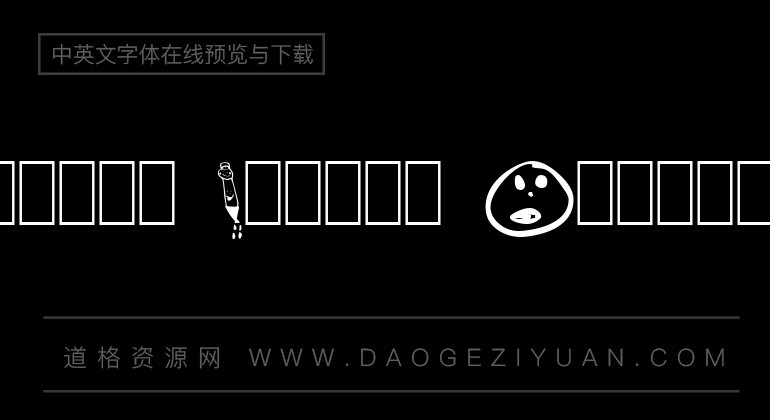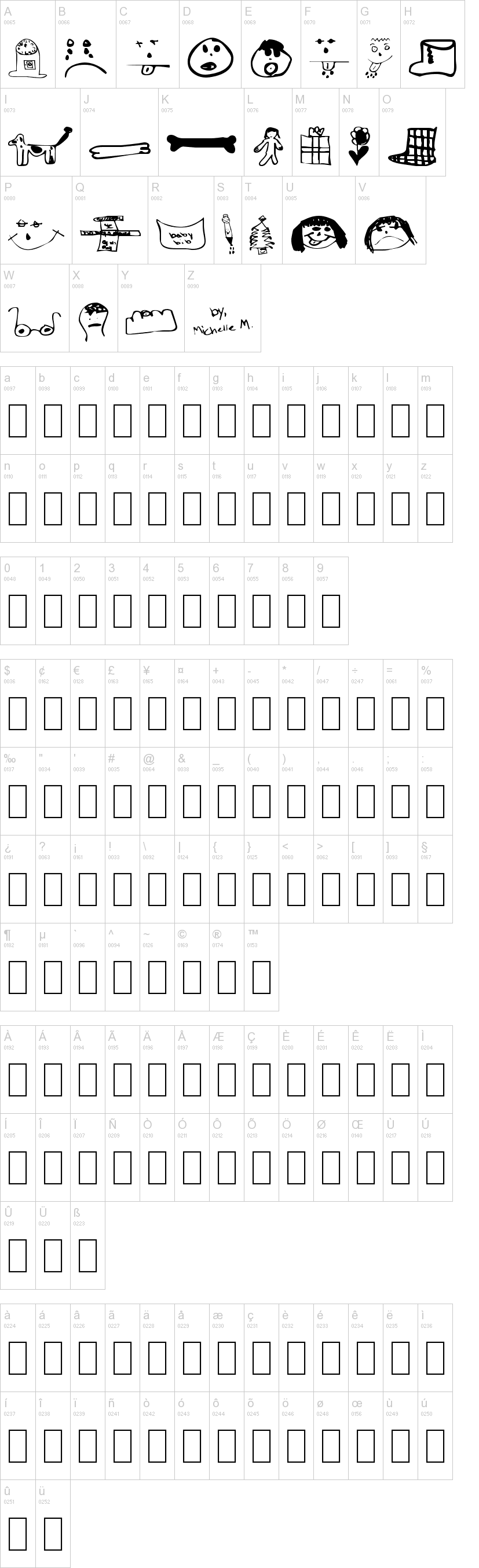
Little Sister Dingbats
Little Sister Dingbats 是一款由设计师Ksenya Zoltsman设计的字体,它是一种绘图字体,包含了64种不同的小图案,每个图案都有它自己的名字。它们是用来表达不同感受和情绪的,比如热情、友好、愤怒、悲伤等等。它们可以用来装饰文本,也可以用作图标,甚至可以用来创建自己的绘图。Little Sister Dingbats字体适用于任何类型的设计,从印刷到网页,都可以使用它。
Little Sister Dingbats是一款非常不错的手写艺术字体,具有很好的视觉感,适合于文化类的宣传设计、商业类品牌的广告和产品包装设计以及个性化文字排版等较多场景。